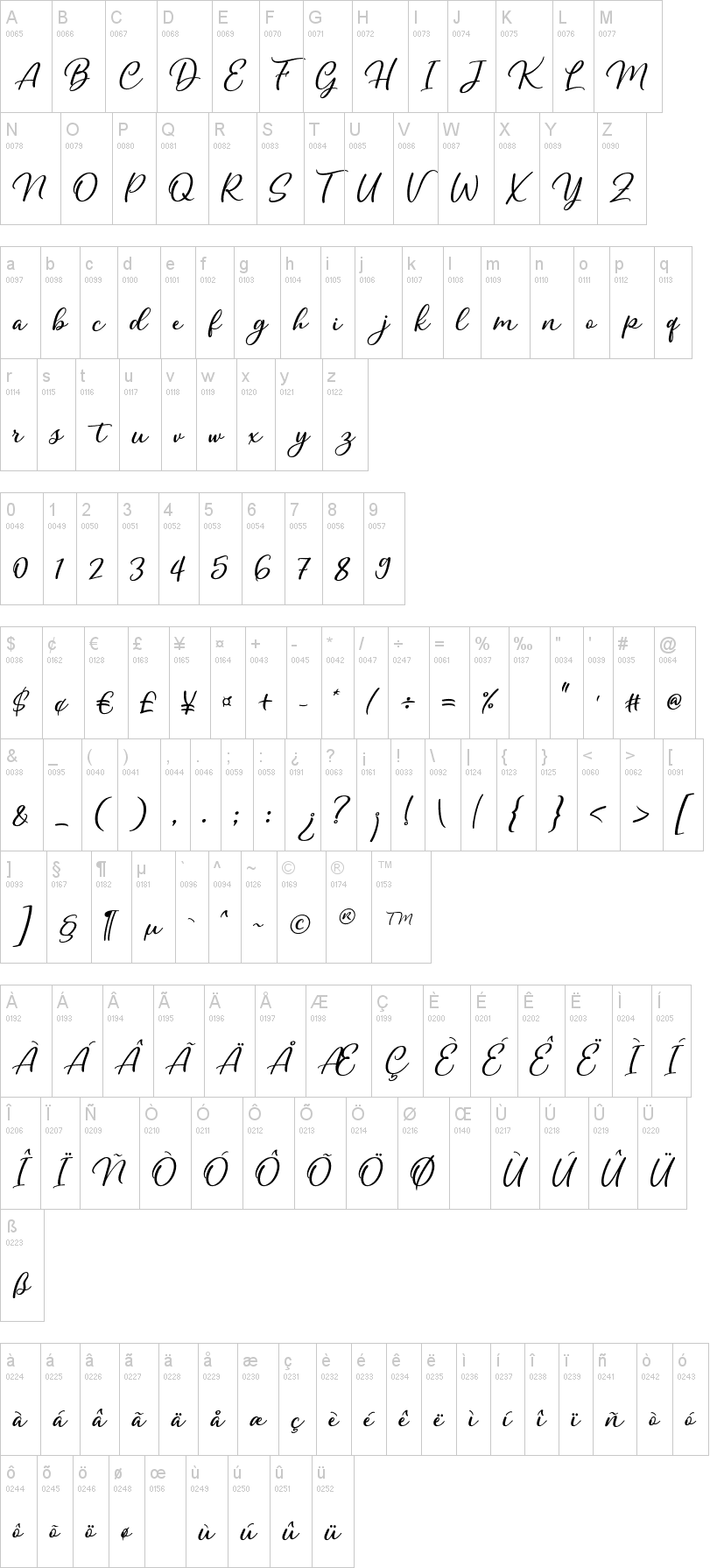
Yukikato是一种日本字体,具有优美的笔画和流畅的曲线。它的名称在日语中意为“雪花”,因此该字体的设计灵感来源于雪花的形态。Yukikato字体的笔画精细而清晰,适合用于标题、标志、海报和其他需要高度可读性和视觉吸引力的设计项目中。该字体具有多个字重和风格选项,可以用于不同的设计需求,例如正式、时尚或创意类项目。总的来说,Yukikato是一种优秀的日本字体,其设计灵感和细节处理都非常出色。内容介绍
Yukikato是一款非常不错的手写艺术字体,具有很好的视觉感,适合于文化类的宣传设计、商业类品牌的广告和产品包装设计以及个性化文字排版等较多场景。